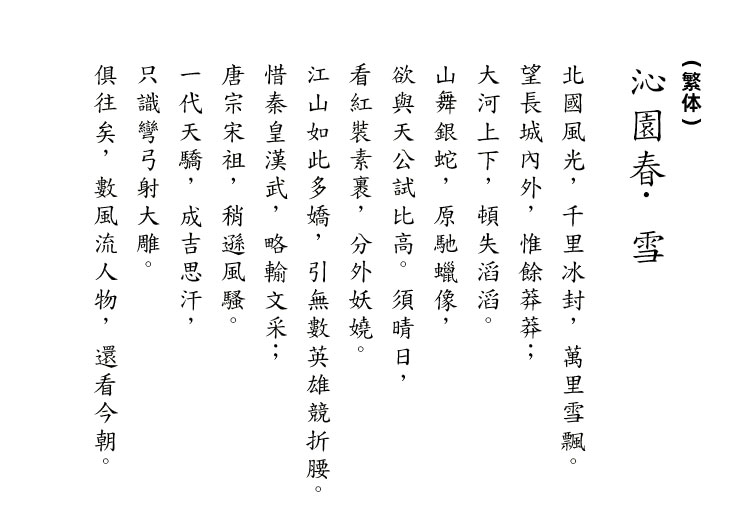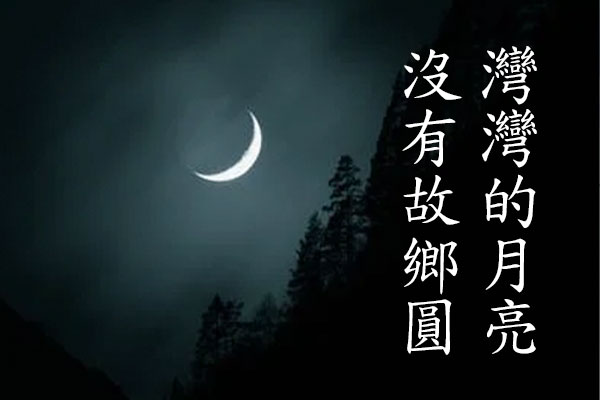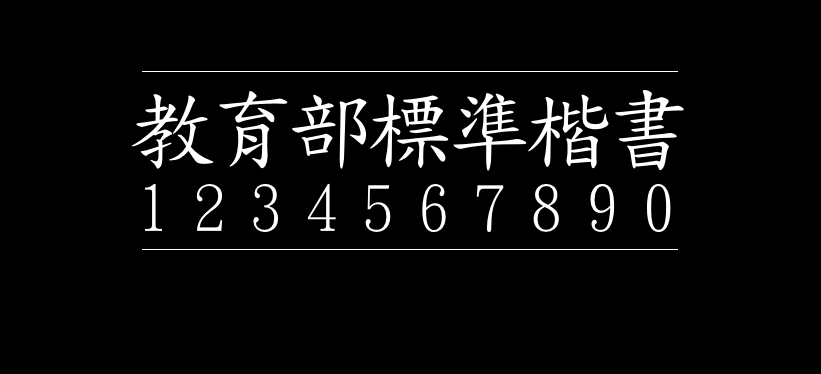
台湾教育部标准楷书
台湾教育部标准楷书(教育部標準楷書)是针对台湾地区而开发一款实用的标准楷书字体,该字体线条粗细适中,整体效果出色,由台湾教育部推出,字形扁方左右分展,化圆为方化弧为直,端正秀美。该字体包含4391个简体中文、字母、 符号和数字,具有古典、中国风、大气 的风格,可以满足您设计上的各种需求。
该字体对由于是台湾地区推出的,对繁体中文支持得较好,而简体有缺字现象。